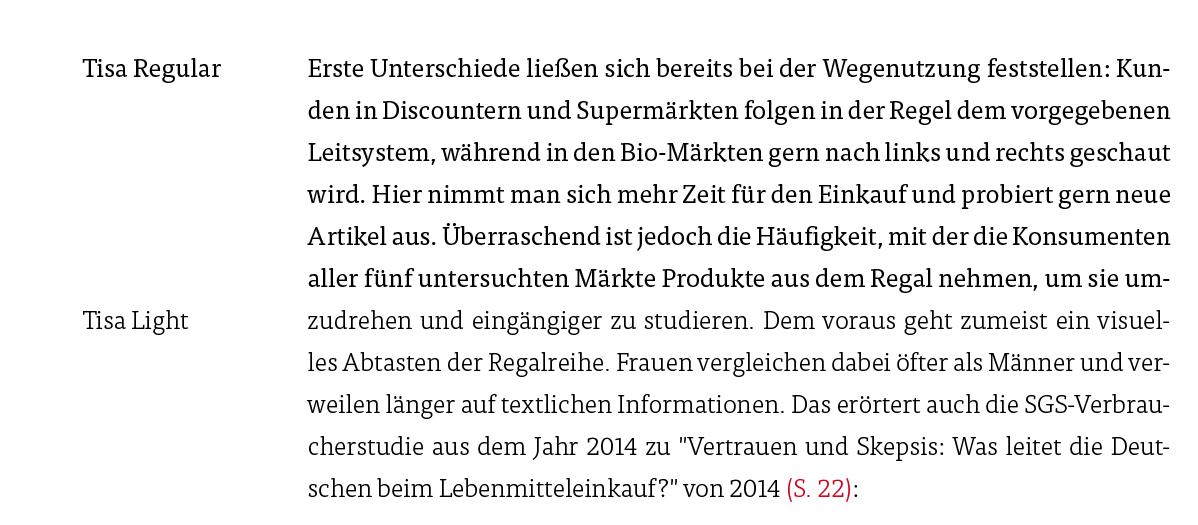
Welcher Tisa-Schnitt eignet sich am besten bei Fließtexten?
ich knabbere gerade am Fließtextproblem und habe mich wahrscheinlich daran übersehen.
Hat jemand unter euch Erfahrung, ob Regular oder Light der Tisa für einen Fließtext lesefreundlicher ist?
Ich würde dann zu light tendieren ...
(und gleich wird sich jemand anderer zu Wort melden und sagen, nein, regular muss es sein.)
Ja, hier, ich! :cheer:
Mit der Regular machst du auf jeden Fall nichts falsch.
Ob die Light auch funktioniert, müsste man im tatsächlichen Druckverfahren testen und im Kontext abwägen – etwa in Hinblick auf die Zielgruppe. Light wirkt etwas eleganter, aber hat natürlich auch einen Tick weniger Substanz für die Erkennbarkeit der Zeichen.
Ob die Light auch funktioniert, müsste man im tatsächlichen Druckverfahren testen und im Kontext abwägen.
Ja das stimmt. Ich habe schon mehrere Papierarten durch den Tintenstrahl-Drucker gejagt und mit Laser drucken lassen. Immer mit anderem Ergebnis. Die Regular schmiert dabei leider etwas und wirkt beinahe bold. Letztendlich soll sie im üblichen Digitaldruck-Verfahren einer Onlinedruckerei bestehen. Die Zielgruppe sind dabei meine Profs. ;) Kommunikationsdesigner, sollte man vielleicht anmerken. :)